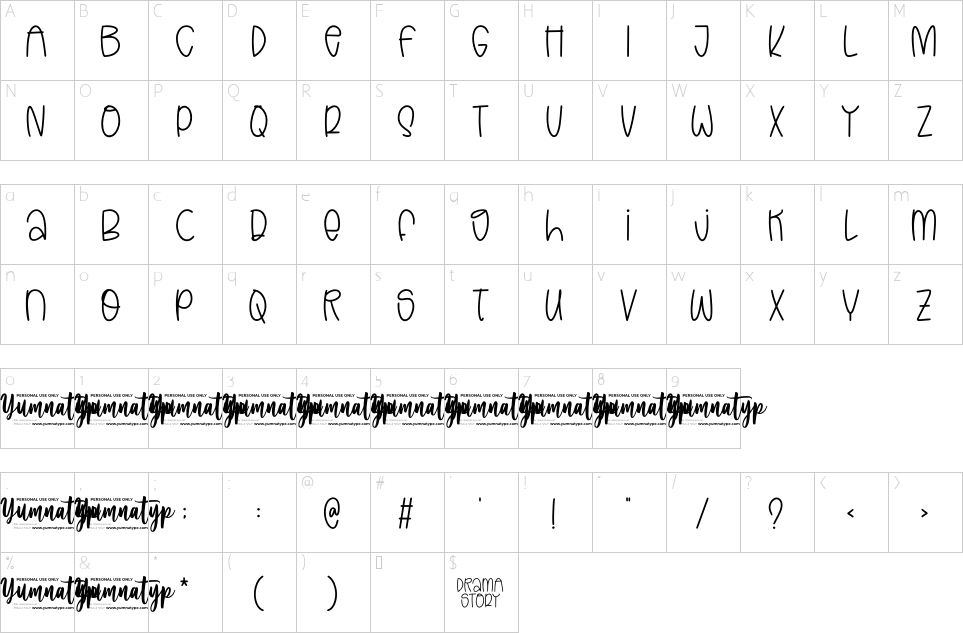
Aqui está uma versão em português para a descrição solicitada sobre a fonte ‘Drama Story Font’: Descubra Drama Story, uma fonte sem custos que transmite intensidade e emoção com suas linhas elegantes e sutis subtilezas. Esta fonte foi projetada por Yumna Type e é perfeita para aqueles que buscam transmitir sentimentos fortes em seu design, seja em materiais digitais ou impressos. Com um design minimalista e sofisticado, ela é ideal para aplicações que exijam uma estética única e poderosa. Download a Drama Story Font para Windows e Mac e inspire-se com sua capacidade de criar expressões distintas em seus trabalhos. Aproveite as muitas possibilidades da Drama Story, que vem embalada com características perfeitas para diferentes cenários design. Esta fonte é uma escolha inteligente para quem busca um recurso gráfico sem custos que traga vida e personalidade a qualquer projeto.